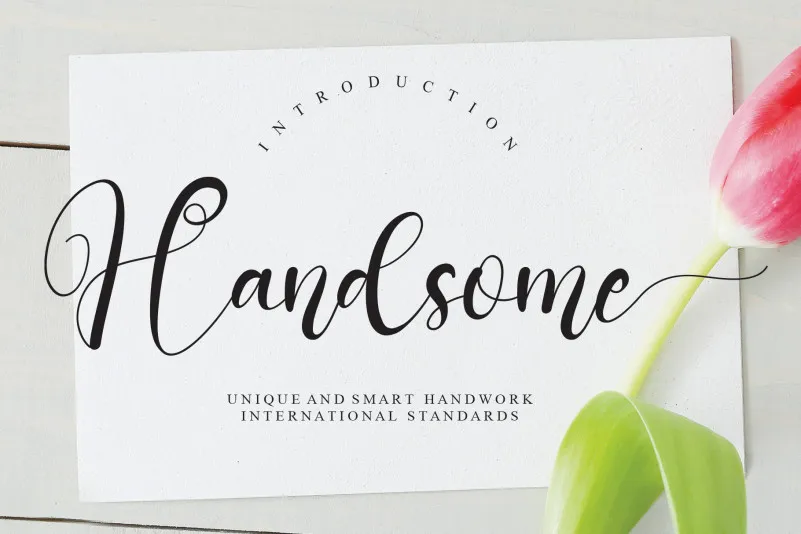
Handsome Font – Download Grátis
Essa é uma fonte escrita a mão com traços círculares, perfeitamente adequada para quem busca algo delicado e elegante. Esta fonte suave será um toque de beleza adicional em diversos projetos gráficos. Ela trará uma sensação de alegria e romance a cada projeto que você criar. Adaptando esta descrição ao contexto do Handwritten Font, para a página de download da ‘Handsome Font’, criamos uma descrição descrevendo como ela pode adicionar um toque especial à sua produção gráfica. Seja em cartazes festivos ou em designs personalizados, essa fonte escrita a mão suave e círcular será seu grande aliado para criar algo único e encantador.